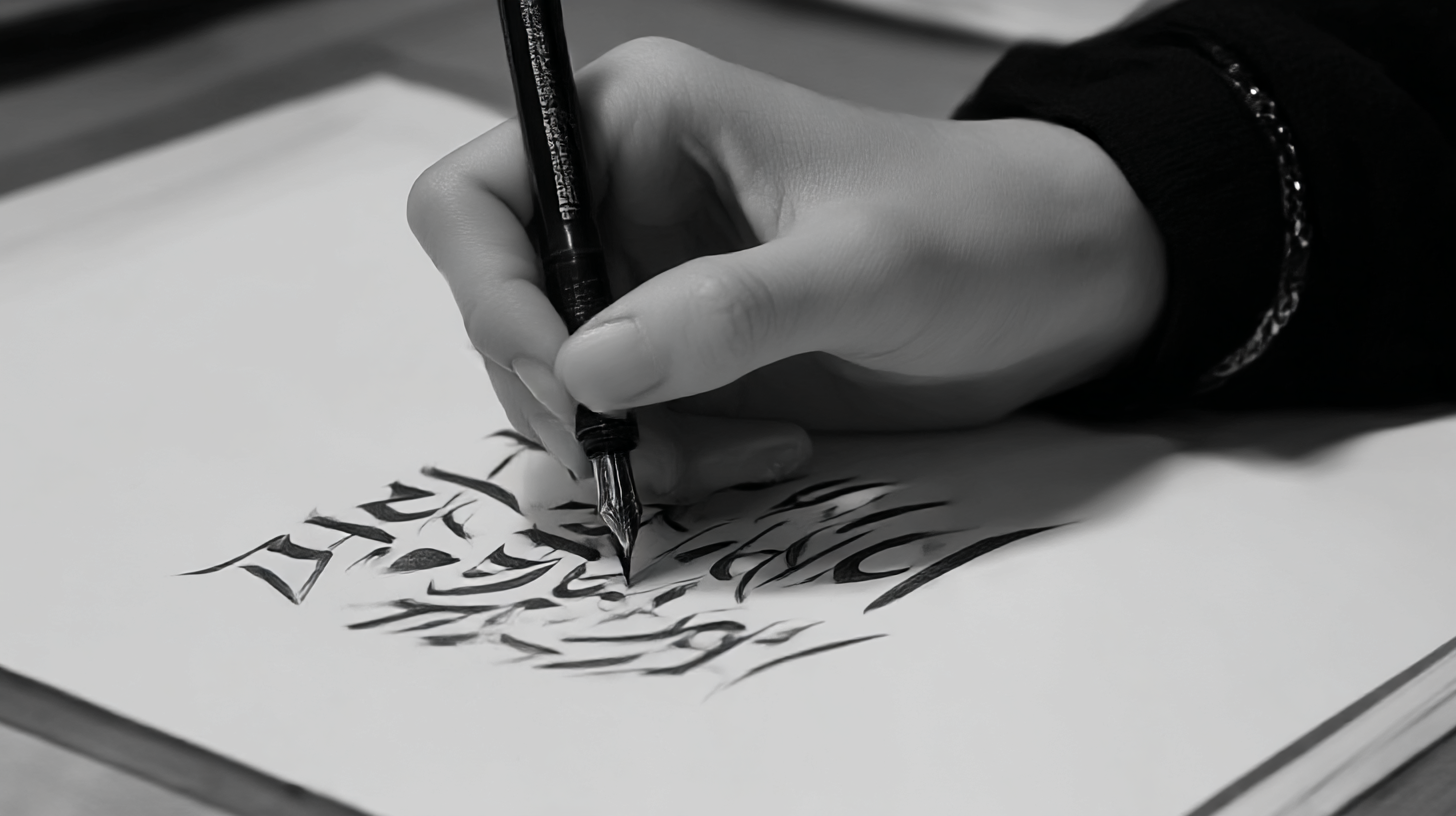
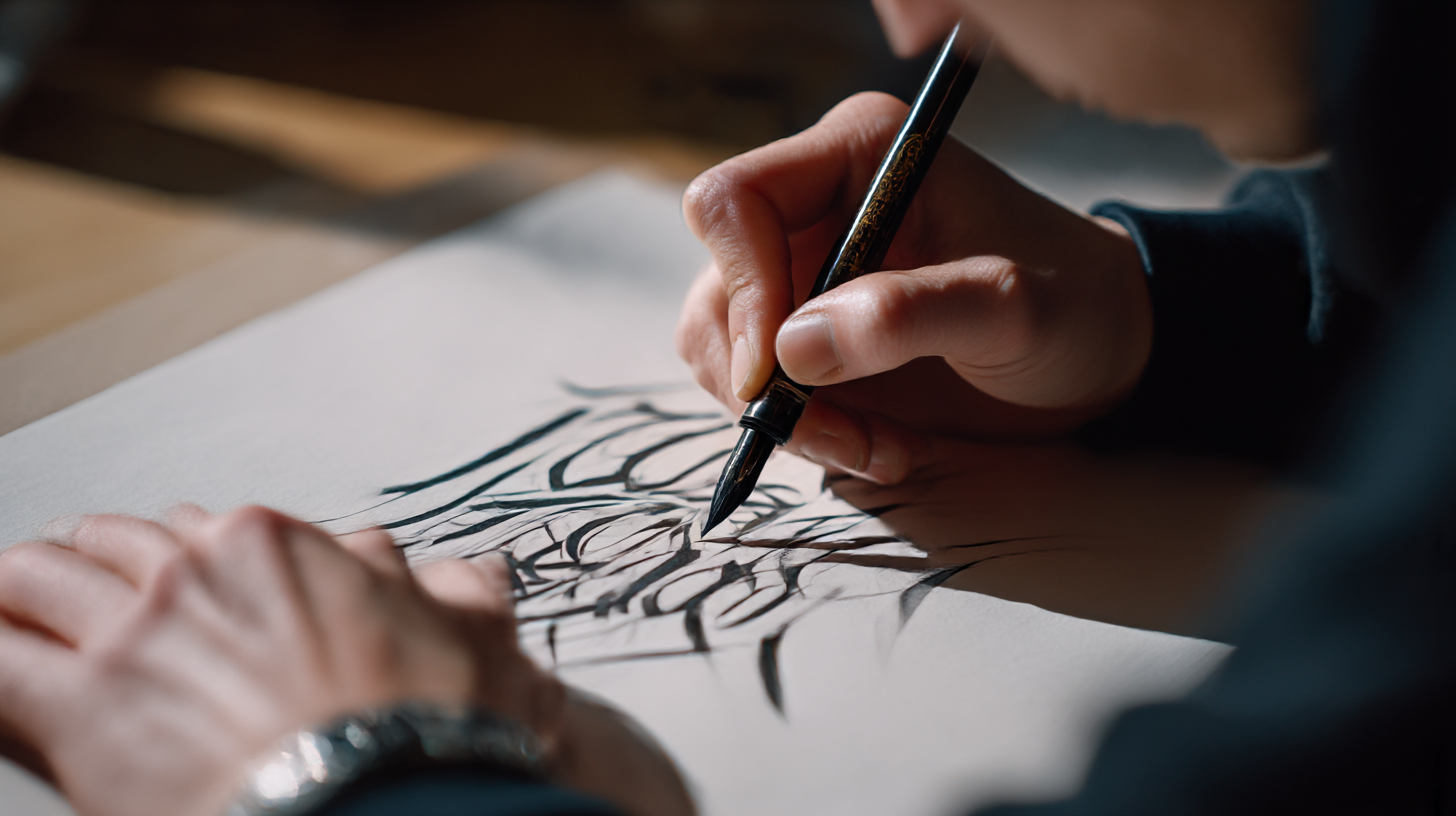
손글씨를 활용한 감성 캘리그래피 연습법 ✍ 손글씨를 활용한 감성 캘리그래피는 단순한 글씨가 아니라 예술적인 표현 방식이에요. 감정을 담아 글씨를 쓰면 단어 하나하나에 특별한 의미가 더해진답니다. 캘리그래피는 다양한 분위기를 연출할 수 있어서 다이어리 꾸미기, 카드 디자인, 포스터 제작 등 여러 방면에서 활용할 수 있어요.
내가 생각했을 때 캘리그래피는 감성을 담아 쓰는 손글씨 그 자체예요. 특별한 기법을 배우지 않아도, 연습을 통해 누구나 감성적인 글씨를 만들 수 있죠. 오늘은 손글씨를 활용해 감성적인 캘리그래피를 연습하는 방법을 알려드릴게요! 🖋✨
이제 캘리그래피의 기본 개념부터 시작해볼까요? 👇
🖋 캘리그래피란 무엇인가?
캘리그래피(Calligraphy)는 손글씨를 활용한 예술적인 글씨 표현 기법이에요. 단순한 필기가 아니라 글씨 자체를 하나의 디자인 요소로 활용하는 것이 특징이죠. 필압, 획의 굵기, 글자의 균형 등을 조절하면서 감성적인 분위기를 연출할 수 있어요. 🎨
캘리그래피는 고대부터 다양한 문화에서 발전해 왔어요. 서양에서는 로마 시대부터 필기체가 발달했고, 동양에서는 서예가 캘리그래피의 한 형태로 자리 잡았죠. 현대에는 디지털 캘리그래피도 인기가 많아지면서 손글씨를 기반으로 한 다양한 디자인이 등장하고 있어요. 🖊
손글씨 캘리그래피는 정형화된 글씨체보다 자유롭고 개성적인 표현이 가능해요. 특히 감성적인 메시지를 담아 쓰면 보는 사람에게 따뜻한 감동을 줄 수 있답니다. 캘리그래피를 활용하면 일기, 다이어리, 카드, 포스터 등을 더욱 감성적으로 꾸밀 수 있어요. ✍💕
📜 캘리그래피와 일반 손글씨 비교
항목 캘리그래피 일반 손글씨 글씨 형태 자유롭고 감성적인 스타일 단정하고 일관된 필기체 필압 조절 강약 조절로 획의 굵기 변화 균일한 굵기의 글씨 활용 용도 포스터, 카드, 디자인 요소 일기, 노트 필기, 문서 작성 이처럼 캘리그래피는 감성을 담아 자유롭게 표현하는 것이 특징이에요! 이제 감성 캘리그래피의 주요 특징을 알아볼까요? ✨
✨ 감성 캘리그래피의 특징
감성 캘리그래피는 단순히 글씨를 쓰는 것이 아니라, 감정을 담아 표현하는 것이 가장 큰 특징이에요. 글자의 크기, 굵기, 획의 흐름을 조절하면서 감성을 극대화할 수 있답니다. 💖
특히 감성 캘리그래피는 자유로운 스타일을 가지고 있어요. 정해진 규칙 없이 손의 감각과 감정을 따라가며 쓰기 때문에 개성이 드러나고, 같은 단어라도 쓰는 사람에 따라 분위기가 달라질 수 있어요. ✍
또한, 감성 캘리그래피는 획의 강약 조절이 중요해요. 획을 부드럽게 빼거나 강조하는 부분을 조절하면 더욱 감각적인 글씨가 완성돼요. 이런 요소들이 모여 감성적인 느낌을 극대화할 수 있죠! 🎨
🖊 감성 캘리그래피와 일반 캘리그래피 비교
특징 감성 캘리그래피 일반 캘리그래피 필기 방식 손의 감각에 따라 자유롭게 표현 정해진 규칙과 서체 유지 획의 강약 자연스러운 굵기 변화 일정한 두께 유지 활용 분야 손글씨 아트, 다이어리 꾸미기, 감성 디자인 브랜딩 로고, 공식 서체 디자인 감성 캘리그래피는 개성을 살릴 수 있는 멋진 스타일이에요! 😍 이제 본격적으로 캘리그래피를 연습하기 전에 필기구를 준비해볼까요? ✨
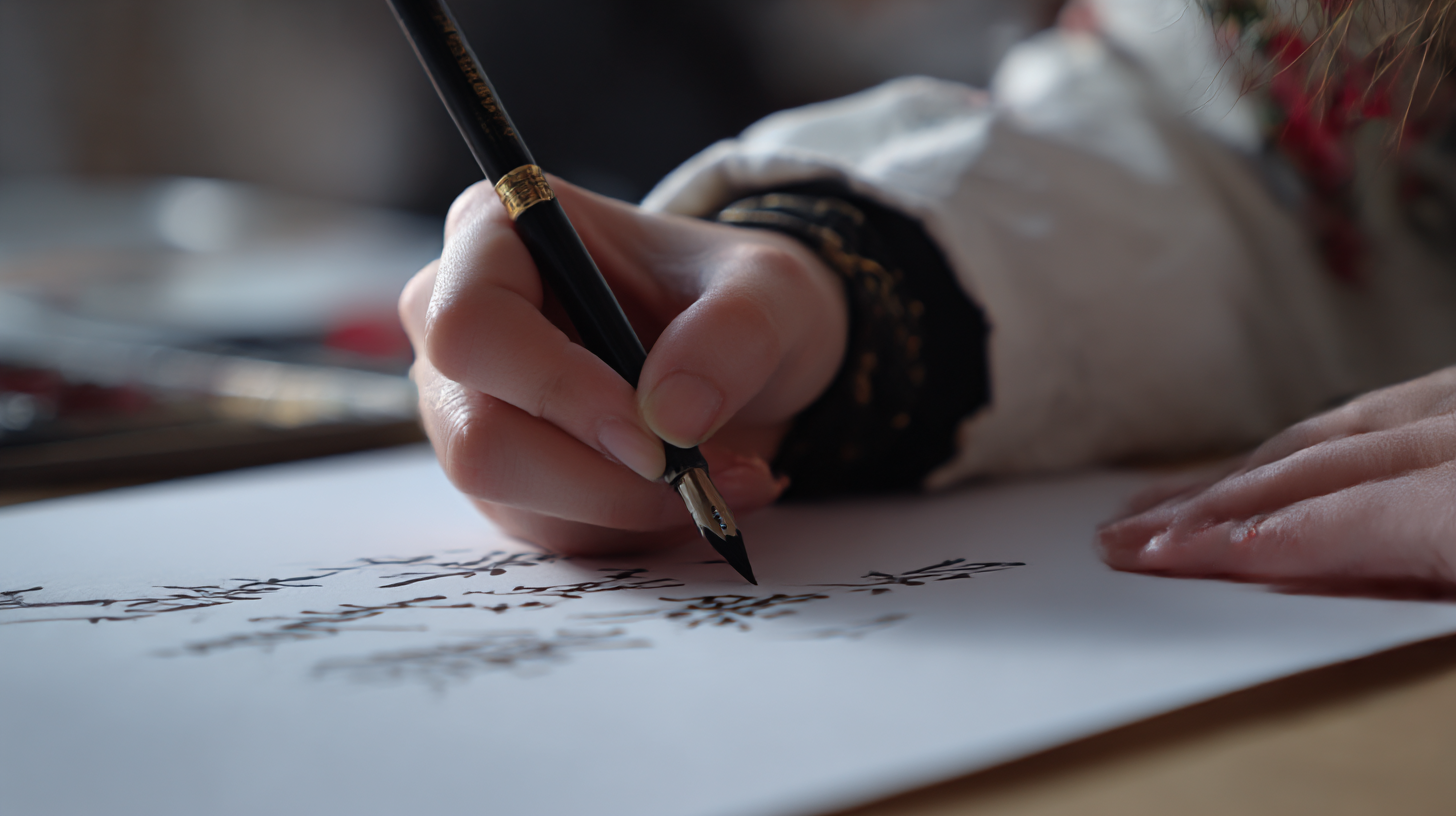
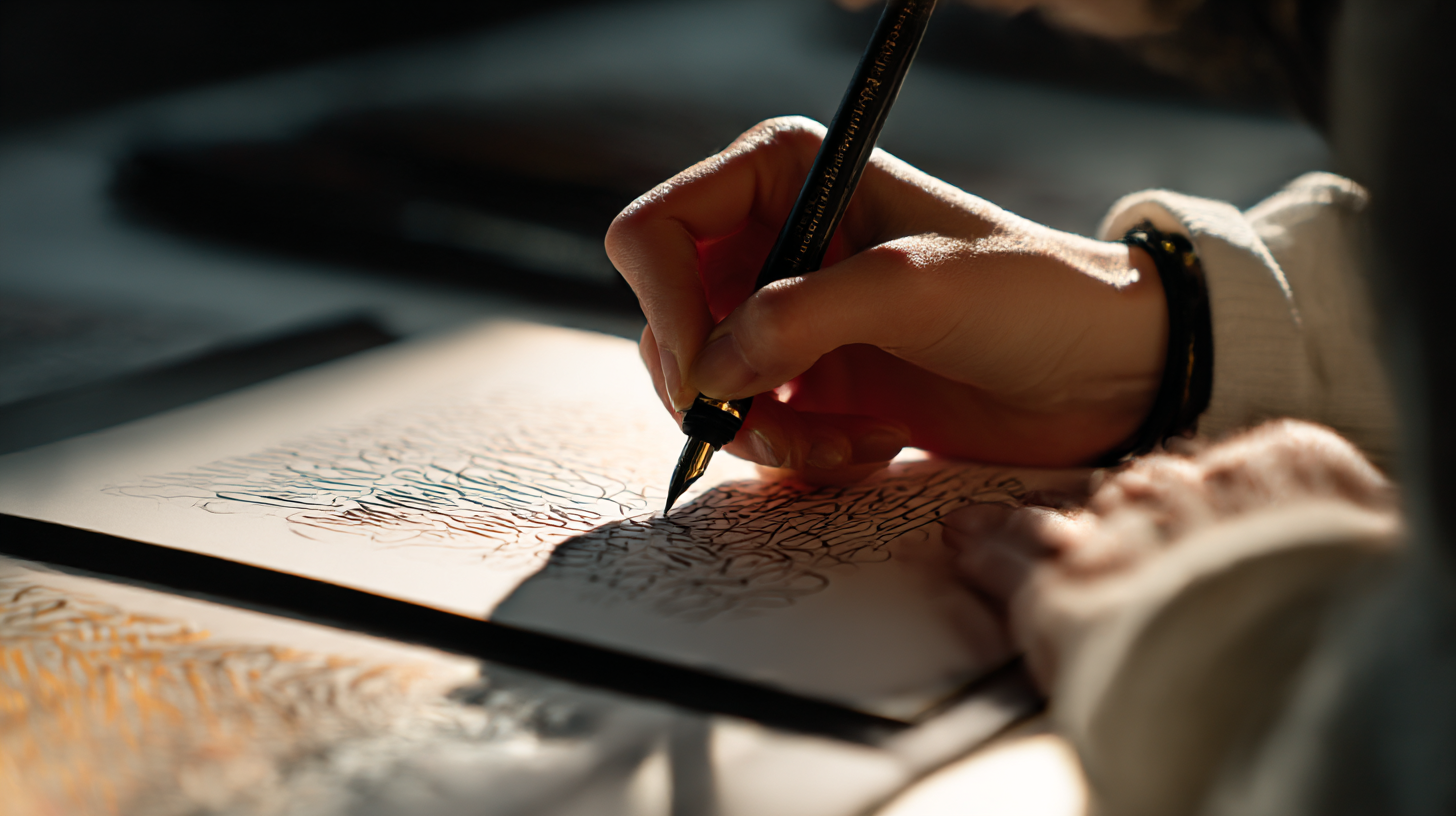
감성 캘리그래피의 특징 🖊 필기구 선택과 준비 과정
감성 캘리그래피를 제대로 연습하려면 적절한 필기구를 선택하는 것이 중요해요. 필기구에 따라 글씨의 분위기가 달라질 수 있고, 획의 강약 조절도 훨씬 쉬워지거든요! ✨
보통 캘리그래피에는 붓펜, 만년필, 젤펜, 딥펜 등을 많이 사용해요. 각 필기구마다 특징이 다르기 때문에 본인의 필기 스타일과 연습 목적에 맞는 도구를 선택하는 것이 좋아요. 🖋
📌 감성 캘리그래피에 적합한 필기구 추천
필기구 종류 특징 추천 용도 붓펜 필압 조절이 가능해 다양한 획 표현 감성적인 손글씨, 캘리그래피 연습 젤펜 부드러운 필기감과 선명한 잉크 손글씨 연습, 다이어리 꾸미기 만년필 부드럽고 우아한 필기체 표현 가능 고급스러운 캘리그래피 작업 딥펜 잉크를 직접 찍어 쓰는 방식 고전적인 캘리그래피 작업 붓펜은 감성적인 캘리그래피 연습에 가장 많이 사용되지만, 만년필과 젤펜도 충분히 활용할 수 있어요! 각 도구의 장단점을 이해하고 본인에게 맞는 필기구를 선택해보세요. 🖋
이제 필기구 준비가 끝났다면, 본격적으로 캘리그래피 기초 연습을 시작해볼까요? ✨
✍ 기초 연습법 & 손글씨 응용
캘리그래피를 잘 쓰기 위해서는 기본적인 필기 연습이 필수예요! 감성적인 글씨를 완성하기 위해서는 손의 힘을 조절하고, 획을 부드럽게 빼는 연습이 필요하답니다. 🎨
연습할 때는 획의 강약 조절, 자간과 행간 맞추기, 곡선 표현 연습 등을 꾸준히 반복하는 것이 좋아요. 처음에는 천천히 쓰면서 균형을 잡고, 점차 속도를 높이는 방식으로 연습하면 좋아요. 🖋
📌 캘리그래피 기초 연습법
연습법 설명 추천 필기구 획의 강약 조절 획의 굵기를 다르게 써보며 감각 익히기 붓펜, 만년필 곡선 연습 알파벳 S나 한글의 ㅇ을 반복해서 써보기 젤펜, 딥펜 자간 & 행간 맞추기 글자 간격을 일정하게 맞추는 연습 연필, 젤펜 이러한 연습을 꾸준히 하면 자연스럽게 손에 익고, 감성적인 글씨체를 만들 수 있어요! ✨
이제 연습한 캘리그래피를 활용해서 다이어리를 꾸미는 방법도 살펴볼까요? 📖💖
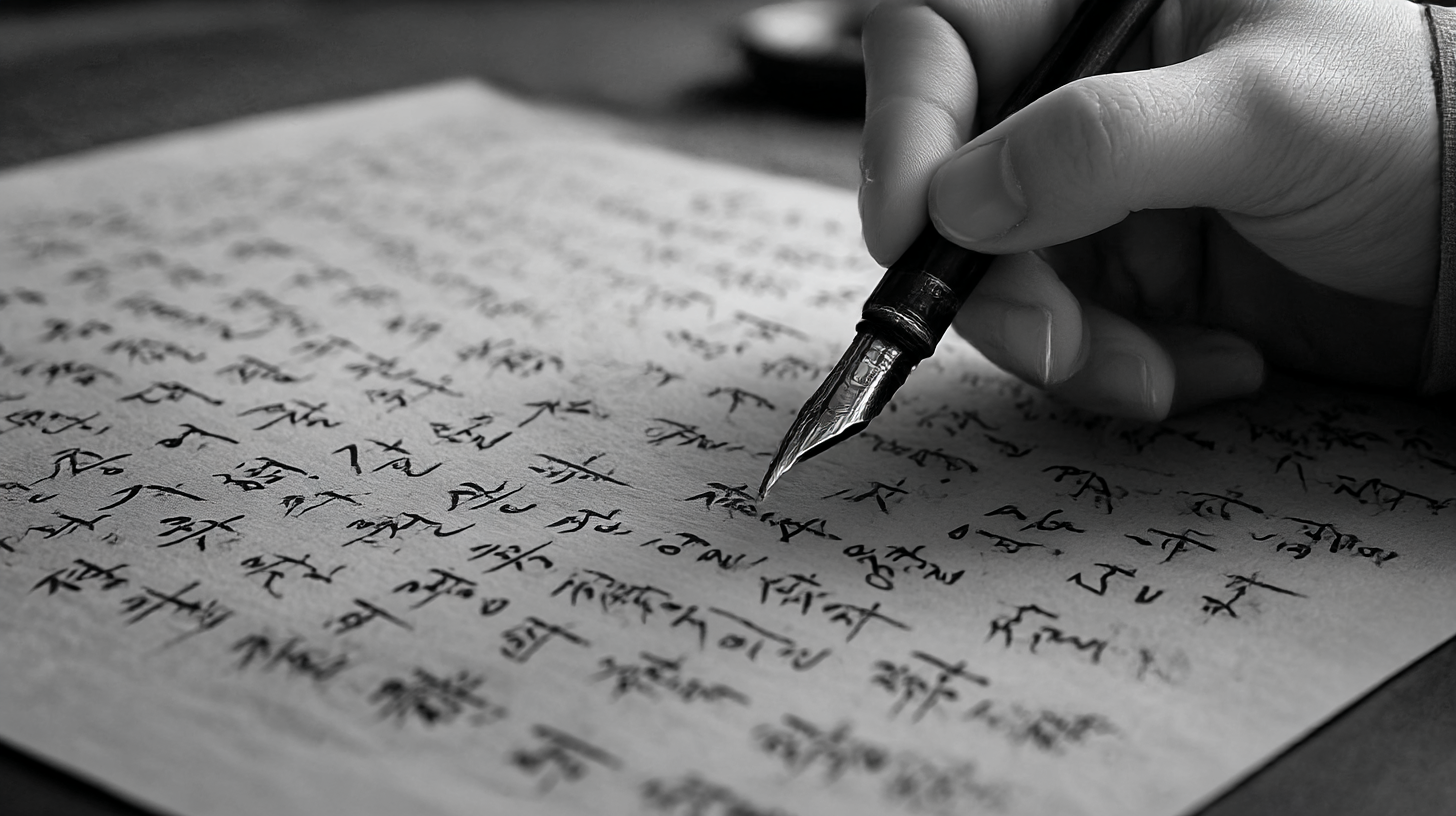
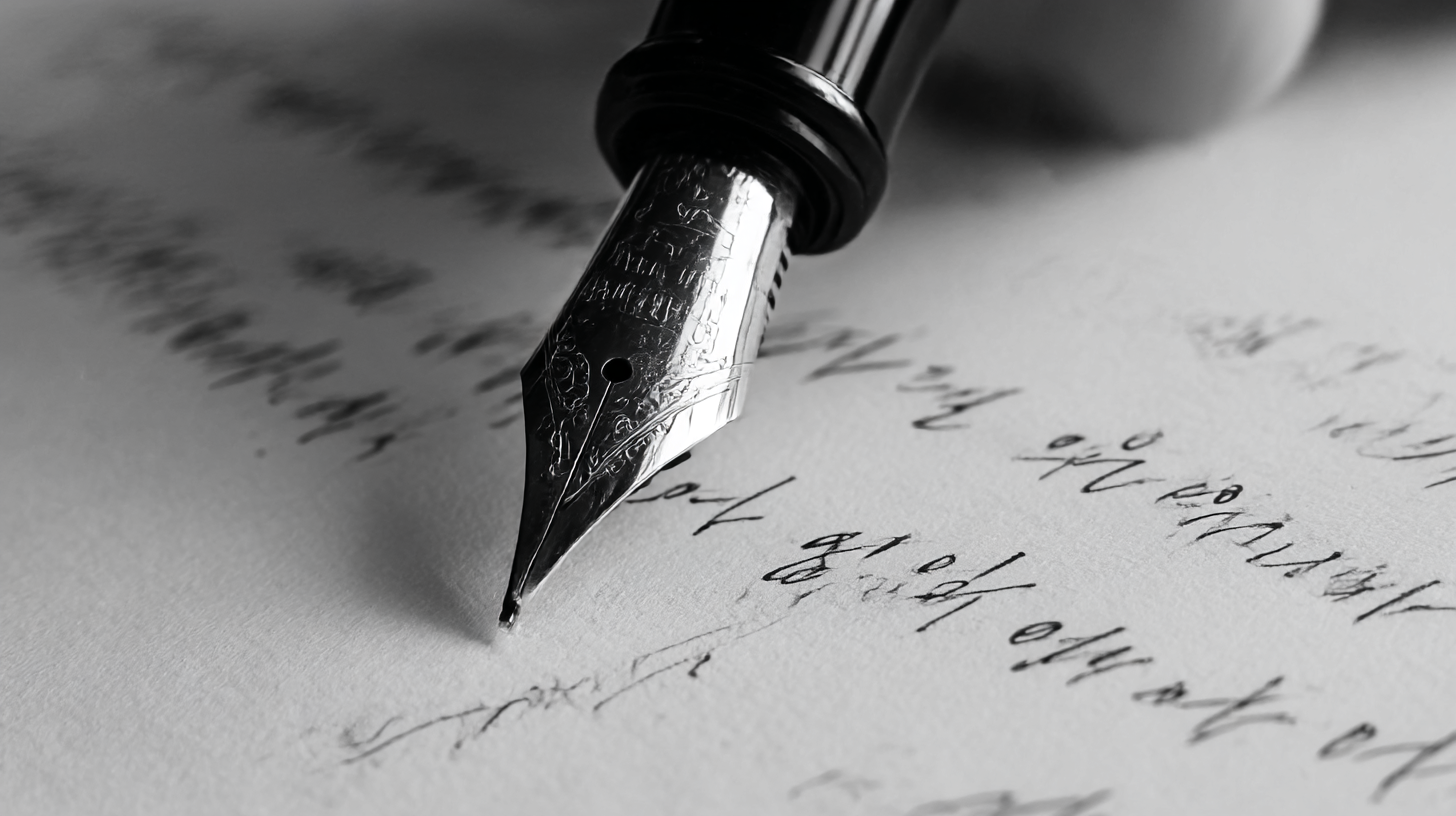
기초 연습법 & 손글씨 응용 📖 캘리그래피를 활용한 다이어리 꾸미기
다이어리는 단순히 기록하는 공간이 아니라, 나만의 감성을 담아 꾸밀 수 있는 특별한 공간이에요. 캘리그래피를 활용하면 더욱 감각적인 다이어리를 만들 수 있답니다! 🖋✨
다이어리 꾸밀 때는 제목, 강조 문구, 감성적인 글귀 등을 캘리그래피로 작성하면 분위기가 확 달라져요. 여기에 마스킹 테이프나 스티커를 살짝 추가하면 더욱 예쁘게 꾸밀 수 있어요! 🎀
🖊 다이어리에 활용할 캘리그래피 요소
활용 요소 설명 추천 필기구 제목 & 날짜 굵은 획으로 강조된 캘리그래피 사용 붓펜, 만년필 중요한 일정 색상 포인트를 준 캘리그래피 활용 컬러 젤펜 감성 문구 감정을 담은 손글씨 스타일 적용 딥펜, 연필 이처럼 다이어리 속 다양한 요소를 감성적인 캘리그래피로 꾸미면 더욱 개성 있는 디자인이 완성돼요! 💖
이제 감성적인 글씨체를 완성하는 꿀팁도 알아볼까요? ✨
💡 감성적인 글씨체 만들기 꿀팁
캘리그래피를 연습할 때 중요한 것은 나만의 개성을 담아 글씨를 쓰는 것이에요! 몇 가지 간단한 연습 방법과 노하우만 익히면 더욱 감성적인 글씨를 완성할 수 있답니다. ✨
특히 획의 흐름을 자연스럽게 조절하고, 글자의 균형을 맞추는 것이 중요해요. 아래 꿀팁을 참고해서 연습해보세요! 🖊
📝 감성 글씨체 연습 꿀팁
꿀팁 설명 획의 강약 조절 획을 시작할 때는 가볍게, 끝낼 때는 부드럽게 마무리하기 글자 크기 조절 중요한 단어는 크게, 보조적인 단어는 작게 써서 리듬감 만들기 곡선 연습 알파벳 S, 한글의 'ㅇ' 등을 반복적으로 써서 부드러운 곡선 만들기 자연스러운 흐름 글씨를 끊지 않고, 한 번의 흐름으로 이어지게 쓰기 이 방법들을 반복적으로 연습하면 자연스럽게 감성적인 캘리그래피가 완성될 거예요! 💖
이제 캘리그래피와 관련된 자주 묻는 질문들을 정리해볼까요? 🧐
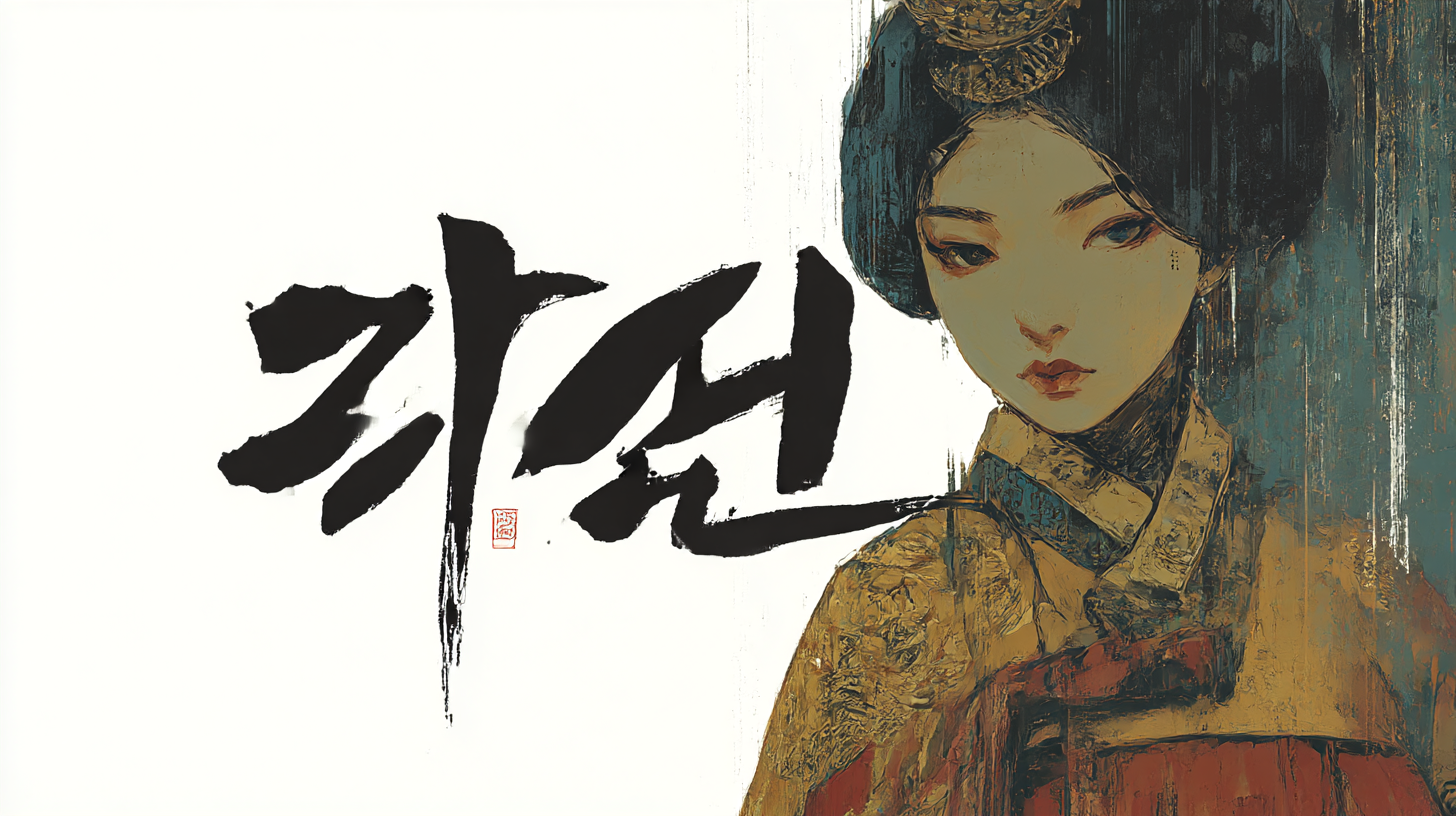
감성적인 글씨체 만들기 꿀팁 ❓ FAQ
Q1. 감성 캘리그래피를 처음 시작하는데, 어떤 필기구를 사용해야 하나요?
A1. 초보자는 필압 조절이 쉬운 붓펜이나 젤펜을 추천해요. 특히 텀보우 후데노스케 붓펜이나 펜텔 터치 붓펜은 감성적인 캘리그래피 연습에 적합하답니다! 🖋
Q2. 캘리그래피를 연습할 때 가장 중요한 포인트는 무엇인가요?
A2. 가장 중요한 것은 획의 강약 조절과 자연스러운 흐름이에요. 글씨를 쓸 때 획의 시작과 끝을 부드럽게 처리하는 연습을 하면 더욱 감성적인 글씨가 완성돼요. ✍
Q3. 다이어리에 캘리그래피를 적용할 때 주의할 점이 있나요?
A3. 다이어리 종이에 따라 잉크 번짐이 생길 수 있으니, 건조가 빠른 젤펜이나 유성 펜을 사용하는 것이 좋아요. 또한 제목과 본문의 글씨 크기를 구분하면 더욱 깔끔한 느낌을 줄 수 있어요! 📖✨
Q4. 캘리그래피를 더 예쁘게 쓰는 방법이 있을까요?
A4. 글자의 크기와 간격을 일정하게 유지하는 것이 중요해요. 또한 감성적인 느낌을 살리려면 곡선 표현을 부드럽게 하고, 단어별로 크기를 다르게 조절해보세요. 🎨
Q5. 캘리그래피 연습을 쉽게 하는 방법이 있을까요?
A5. 먼저 기본 획 연습을 충분히 한 후, 짧은 단어부터 연습하는 것이 좋아요. 그리고 다양한 폰트를 참고하며 자신의 스타일을 찾아가는 과정이 필요해요. 🖊
Q6. 필압 조절이 어려운데, 쉽게 조절하는 방법이 있을까요?
A6. 손에 힘을 너무 주지 말고, 부드럽게 눌렀다가 힘을 빼는 연습을 해보세요. 처음에는 천천히 쓰면서 강약 조절을 익히는 것이 좋아요. ✨
Q7. 손글씨를 감성적으로 꾸미는 데 도움이 되는 아이템이 있을까요?
A7. 마스킹 테이프, 스탬프, 감성적인 스티커 등을 활용하면 더욱 분위기 있는 다이어리를 만들 수 있어요. 또한 파스텔톤 컬러 펜을 사용하면 부드러운 감성을 살릴 수 있답니다. 🎀
Q8. 캘리그래피를 꾸준히 연습하려면 어떻게 해야 하나요?
A8. 매일 짧은 문장을 써보는 습관을 들이는 것이 좋아요! 또한 다이어리나 노트에 하루 한 줄씩 감성적인 문구를 써보면 실력이 자연스럽게 향상된답니다. 📝